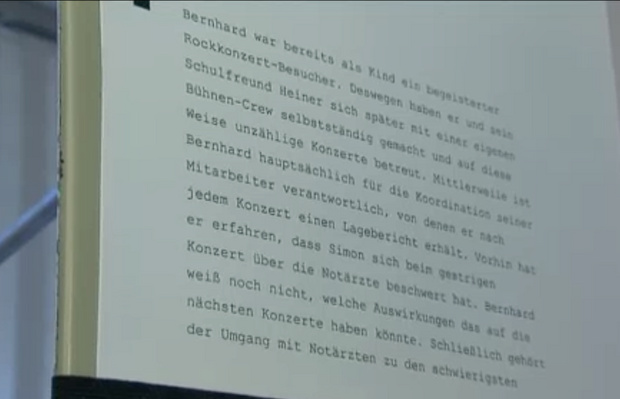
Lesbarkeit Bücher vs. eBooks
Lach.
Wieder mal ein Fall von "Experten bedienen Auftraggeber" oder was? Bzw. welche Studie, Herr Stempfle?
Hab’s auch grad gesehen.
Haben die da wirklich nur getestet, ob man eine halbe Seite monospaced Schrift besser mit nem Tablet lesen kann? Das halte ich nur für bedingt aussagekräftig.
Zumal der eBook-Markt ja eigentlich nicht Tablets sondern eReader anspricht. Die haben dann keine Hinertgrundbeleuchtung, aber war das nicht laut Studie das tolle am Tablet?
Dass die Studie in diesem Sinne »gekauft« war, würde ich noch nicht einmal behaupten wollen. Für mich ist sie nur etwas nach dem Motto »Thema verfehlt«, da wie bei vielen anderen Lesbarkeitsstudien auch, schon der Versuchsaufbau zu wünschen übrig lässt.
Man testet diesen großen, querformatigen Text in Courier(!) mit riesiger Schriftgröße und riesigen Zeilenabständen mal auf einen Blatt und mal auf einem Tablet-Gerät. Das entspricht weder dem normalen Lesen einen Taschenbuches, noch dem typischen Lesen eines eBooks auf Kindle oder iPad.
Der einzige testbare Parameter ist hier die auch im Film angesprochene (Hintergrund-)Beleuchtung. Aber das fände ich jetzt eher noch für Schildermacher interessant. Ein echter Vergleichstest zwischen Buch und eBook ist das nicht, da die Versuchsanordnung viel zu weit davon entfernt ist. Und was bedeutet schon »eBook«? Die im Film auch gezeigten Kindles funktionieren ja schon wieder ganz anders, als die hinterleuchteten Tablets aus der Studie. Diesen Unterschied hätte man zum Beispiel mal untersuchen können.
Aussage: Wir brauchen nicht so viel Aufwand (geringere Gehirnaktivität) die Information zu verarbeiten, also fällt das Lesen leichter.
Kann man auch so interpretieren: Das Leserlebnis ist so dumpf, das sich weniger Regionen im Gehirn angesprochen fühlen, also weniger Aktivitäten messbar sind.
Dieses bewahrende Lesen, das Lesen im Buch, dass viele Generationen als positiv empfunden haben ... Jetzt geht es (auch) darum offen zu sein, eBooks zu ermöglichen.
Hä, what is this?! Und das vom Leiter des Instituts für Buchwissenschaft, Mainz.
Ja klar, jetzt geht es darum die Bücher in Nullen und Einsen für eBooks zu verkaufen., am besten zusätzlich zum schon erworbenen Buch oder Hörbuch.
Soll diese Studie wirklich an nur einer Person durchgeführt worden sein, die zuerst einen Text auf einem Blatt Papier zu lesen bekommt, um dann den gleichen noch einmal auf einem Tablet nachzulesen?
Warum lässt man die Person gerade einmal einen Absatz lesen? Was sagt dies über das Lesen von Büchern bzw. Ebooks über mehrere Stunden aus?
Woher kommt das Fazit am Ende des Beitrags, dass man auf einem Tablet u. a. schneller lesen kann?
Ich kann mir schwer vorstellen, dass diese Studie in dieser Form an einem so renommierten Institut wie das Mainzer Institut für Buchwissenschaft stattgefunden hat.
Mal was anderes: Ich finde fragwürdig, dass das schnellere Lesen auf dem Tablet als Fortschritt gepriesen wird. Die Frage ist doch: verarbeiten, beziehungsweise verstehen die Leute auch in gleicher Qualität, was sie da lesen? Wenn weniger Hirnaktivität gemessen wird als beim Lesen des gedruckten Textes würde ich ja mal ketzerisch annehmen, dass das nicht der Fall ist. Oder anders gesagt: Die Probanden haben für den Test den Text zwar mechanisch gelesen – aber haben sie dies mit der Intention getan diesen inhaltlich zu erfassen? Und noch etwas: Sollte der Text der gedruckten und der elektronischen Vorlage identisch sein, wäre es dann nicht logisch, dass das zweite Drucklesen schneller geht und mit weniger Hirnaktivität verbunden ist? :-?
Danke! Das beseitigt schon ein paar Unklarheiten. Und ganz so eindeutig wie im Fernsehbeitrag beschrieben fallen die Vorteile für das eine oder das andere Medium ja dann wohl doch nicht aus.
Dem wollte ich auch gar nicht widersprechen. Interessant fand ich aber, dass die Gruppe, die laut des von Dir verlinkten Tests am meisten von den eBooks profitieren würde, nämlich die der älteren Menschen, laut der Stern-Studie noch den größten Abstand von der neuen Technologie nimmt. Aber klar – das Diffusionsmodell greift natürlich auch da. :-)
„Ob analog oder digital, Lesen bleibt die wichtigste Kulturtechnik“ steht in dem Fazit der Untersuchung der Mainzer Uni. Das ist ein bemerkenswerter und wahrscheinlich ebenso diskussionswürdiger Satz. Ich persönlich glaube, die Bedeutung des geschriebenen Wortes ist bereits merklich zurückgegangen und wird noch weiter schrumpfen. Vielleicht auch wird Lesen wichtiger als Schreiben?
Ich persönlich glaube, die Bedeutung des geschriebenen Wortes ist bereits merklich zurückgegangen und wird noch weiter schrumpfen.
Und was veranlasst Dich zu dieser Aussage?
Die Zahlen sprechen eine ganz andere Sprache. Überleg mal, wie sich in den letzten Jahrhunderten die Alphabetisierung der Menschen entwickelt hat. Es wird immer mehr gelesen und daher auch immer mehr publiziert. Und die jungen Leute sorgen heute für 250 Millionen Twitter-Nachrichten an JEDEM Tag. Tendenz ständig steigend.
Das mag mancher vielleicht als belangloses Zeug abtun, dass man ja nicht mit Goethe-Texten vergleichen kann, aber eine Nutzung der Kulturtechnik Lesen ist es par excellence.
beachtest du dann auch den absatz von druckern und kopierern?
Nein, das habe ich nicht. Das war nur so aus dem Kopf geschrieben. Vielleicht sollte man den Papierverbrauch pro Nachrichtenmedium ermitteln. Der BVD könnte dazu Zahlen haben.
druckmaschinen als indikator für die wichtigkeit geschriebenen wortes zu nehmen ist arg einseitig. zumal das internet ohne schrift auch nicht denkbar ist.
Das ist natürlich richtig. Während meiner Ausbildung habe ich mich gefragt, ob es wohl eines Tages den Beruf des „Schnellsprechers“ geben könnte.